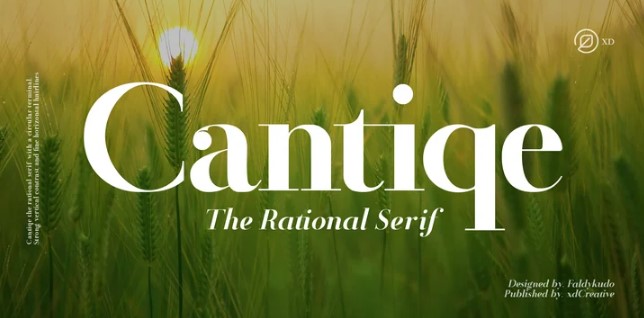
Myfonts Cantiqe Font 2021
[Myfonts] Cantiqe Font (2021)
Cantiqe рациональная засечка с круглым/шаровидным окончанием и сильным вертикальным контрастом и тонкими горизонтальными линиями, Это делает Cantique сочетанием элегантного и красивого.
Cantiqe невероятно универсален, он идеально подходит для модного брендинга или редакционного дизайна. этот шрифт подходит для широкого круга дизайнов, поднимая их на самый высокий уровень. Добавьте этот шрифт к своим любимым творческим идеям и заметите, как он их оживит!